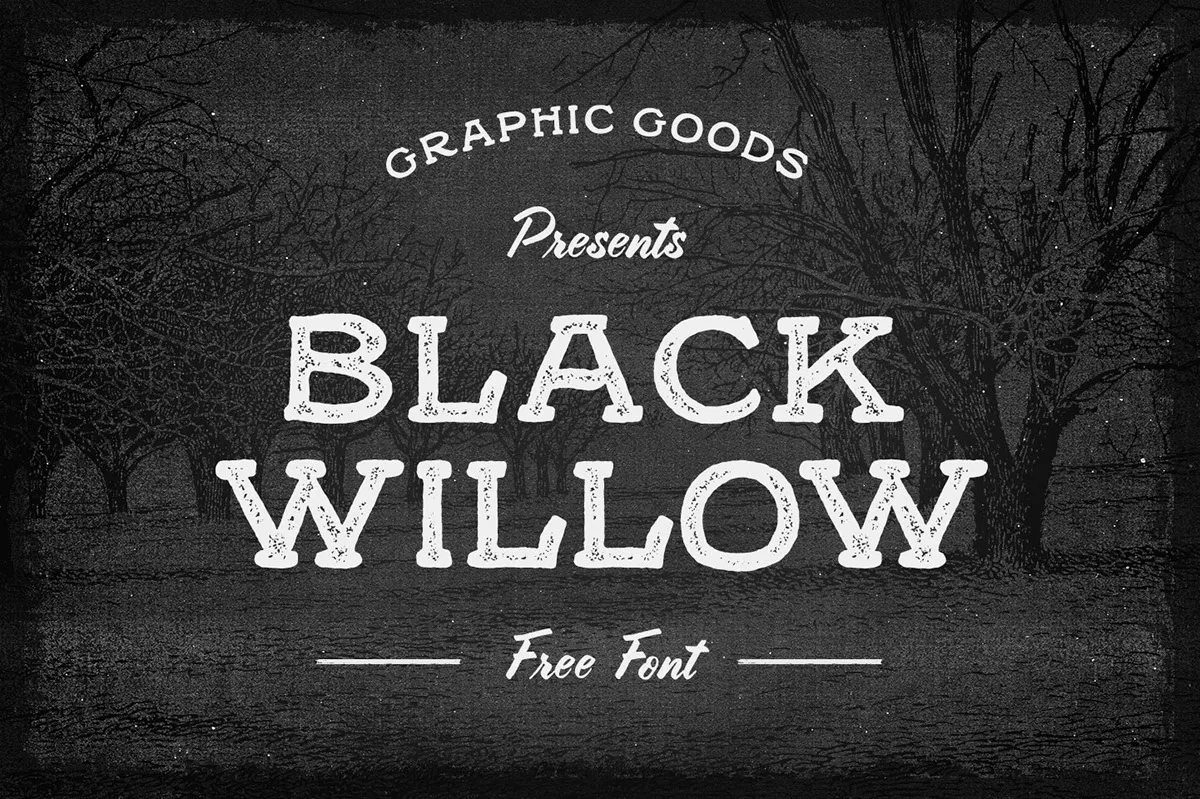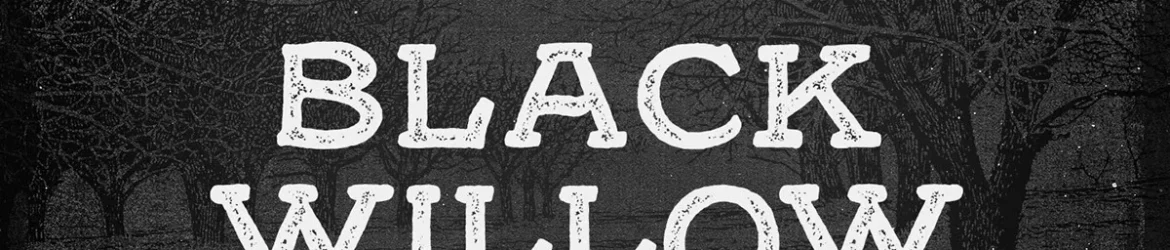
Black Willow Font – Download Grátis
A fonte ‘Black Willow’ é uma elegante escolha para adicionar um toque único a qualquer projeto gráfico. Inspirada nos traços delicados e rusticos dos cartazes e cartões de apresentação manuscritos do passado, ela traz uma atmosfera vintage e autêntica à sua criação. ‘Black Willow’ é uma fonte livre com duas opções de estilo: Regular e Rough. Em seu Regular style, a tipografia mantém um ar delicado e suave, ideal para aplicações como nomes de empresas ou elementos de design gráfico que precisam ser elegantes e sutis. Já o Rough style traz uma sensação mais robusta e quase manuscrita, perfeito para textos em estilos mais alternativos ou para criar um visual único em materiais impressos. A versatilidade desta fonte faz dela uma ótima opção tanto para projetos pessoais quanto comerciais. Este é um excelente recurso para quem busca adicionar um toque autêntico e personalizado a qualquer projeto que faça parte da sua identidade visual, seja em redes sociais, material de marketing ou até mesmo em um design gráfico mais elaborado. ‘Black Willow’ não apenas adiciona uma característica única à sua criação, mas também promove um uso responsável e sustentável. Como é uma fonte gratuita, ela permite que você explore os limites criativos sem necessariamente comprometer seus recursos financeiros. Com Hamilton como seu designer, esta fonte consegue capturar o espírito da arte vernacular dos tempos modernos.